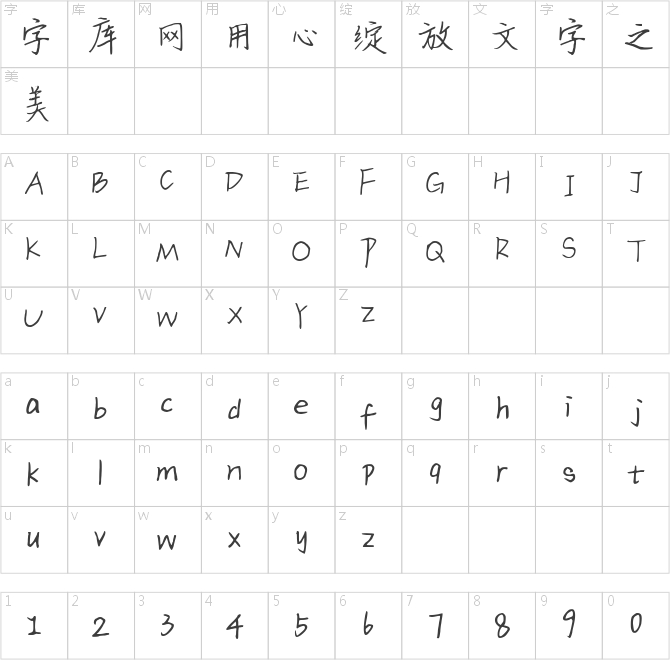
紫竹語(yǔ)嫣 詳情頁(yè)
字體名稱: 紫竹語(yǔ)嫣
紫竹語(yǔ)嫣
紫竹語(yǔ)嫣介紹
紫竹語(yǔ)嫣字體字庫(kù)是一款讓人賞心悅目、百看不厭的中文字體,適合各類廣告和產(chǎn)品包裝設(shè)計(jì)應(yīng)用,字體大小6.57MB,格式為ttf字體,上傳用戶是三極字庫(kù),作者/版權(quán)方為三極字庫(kù)